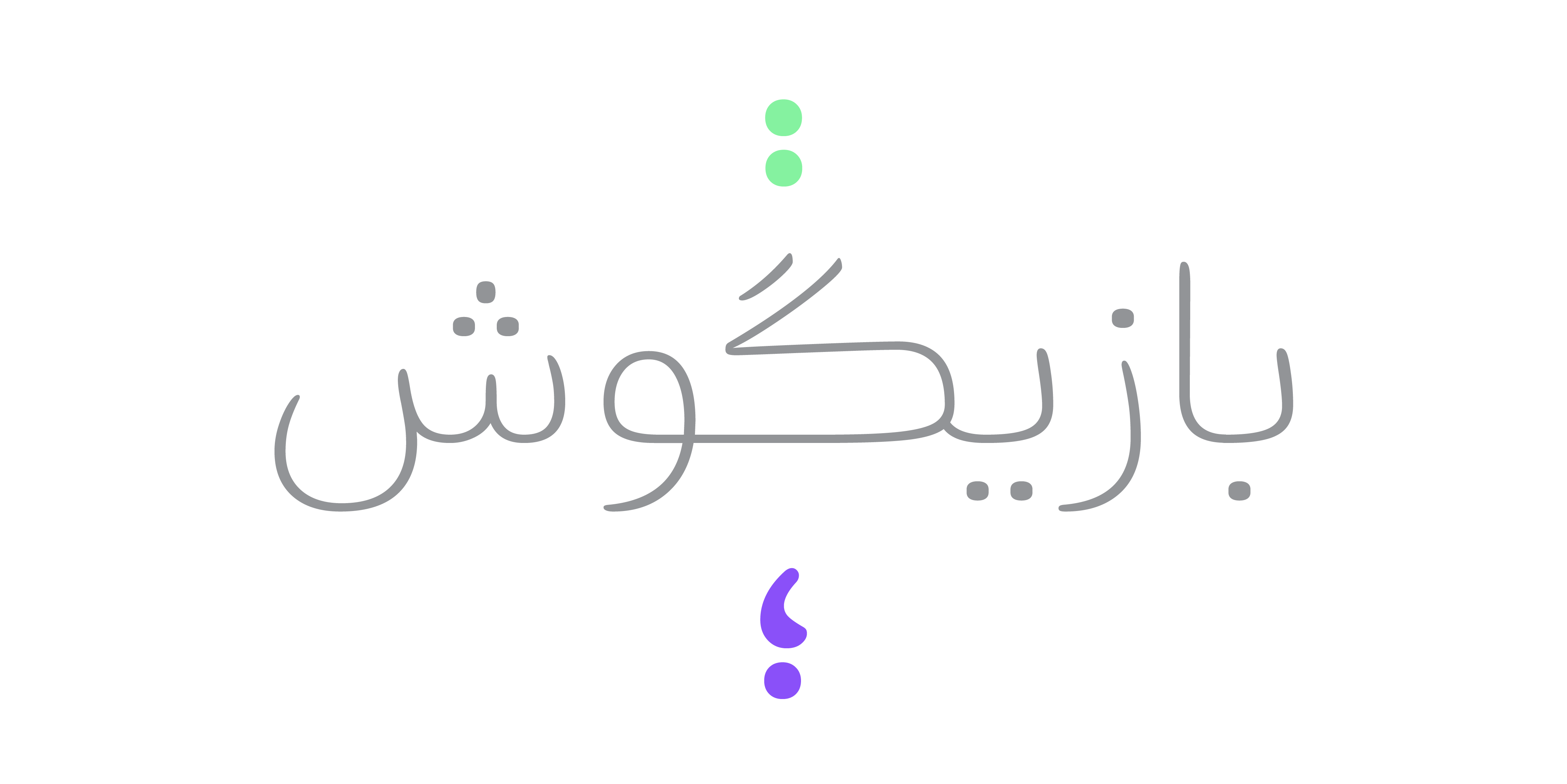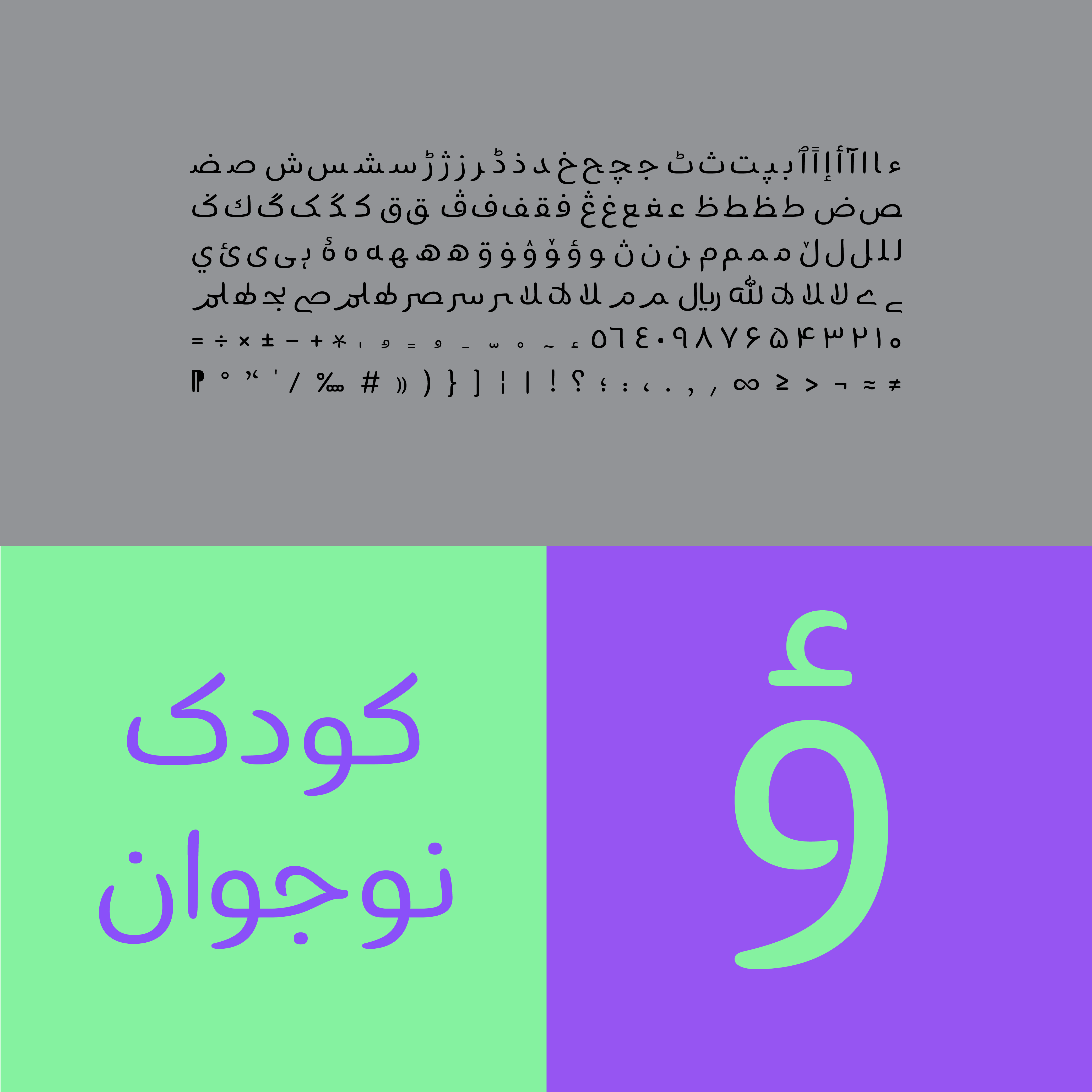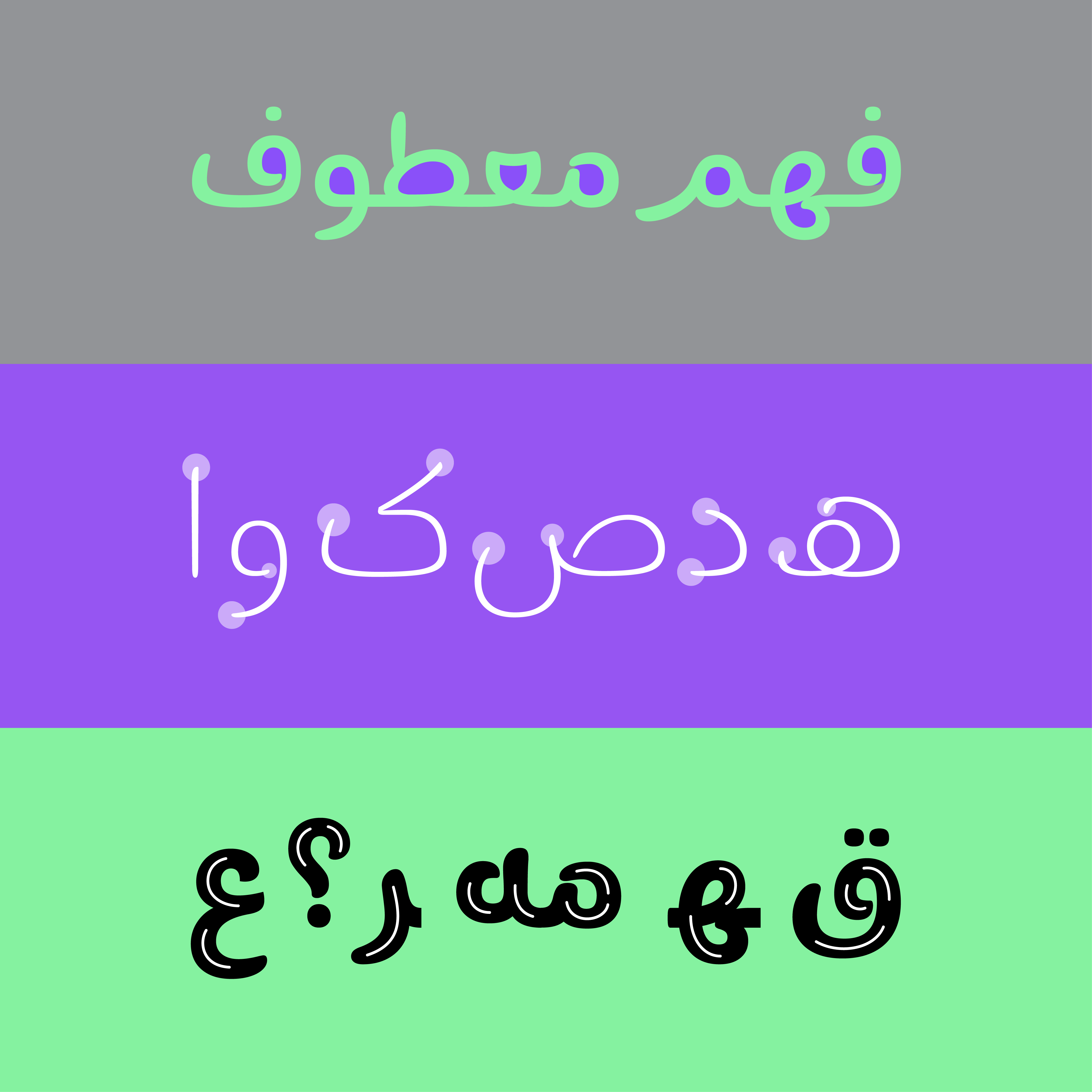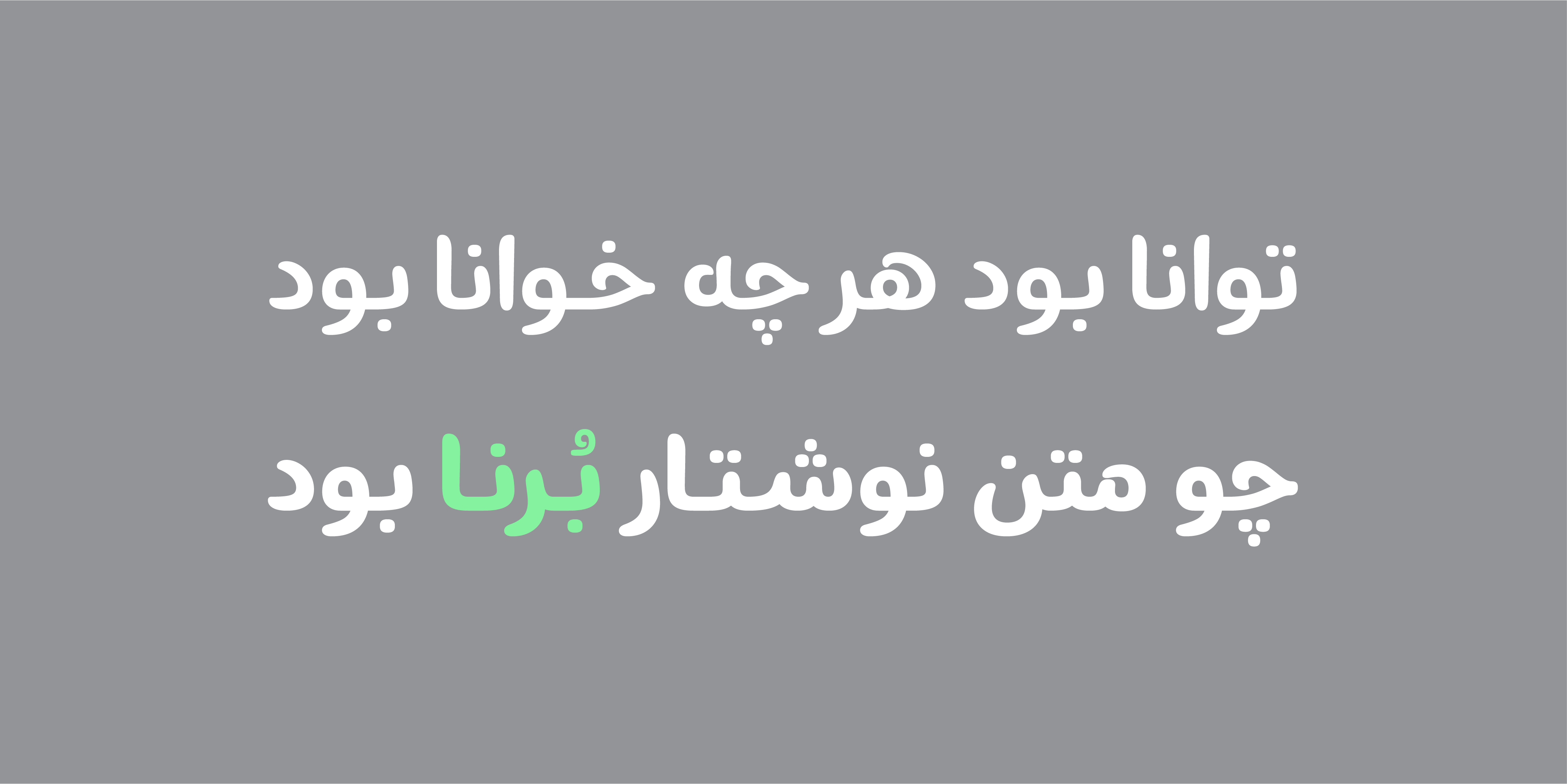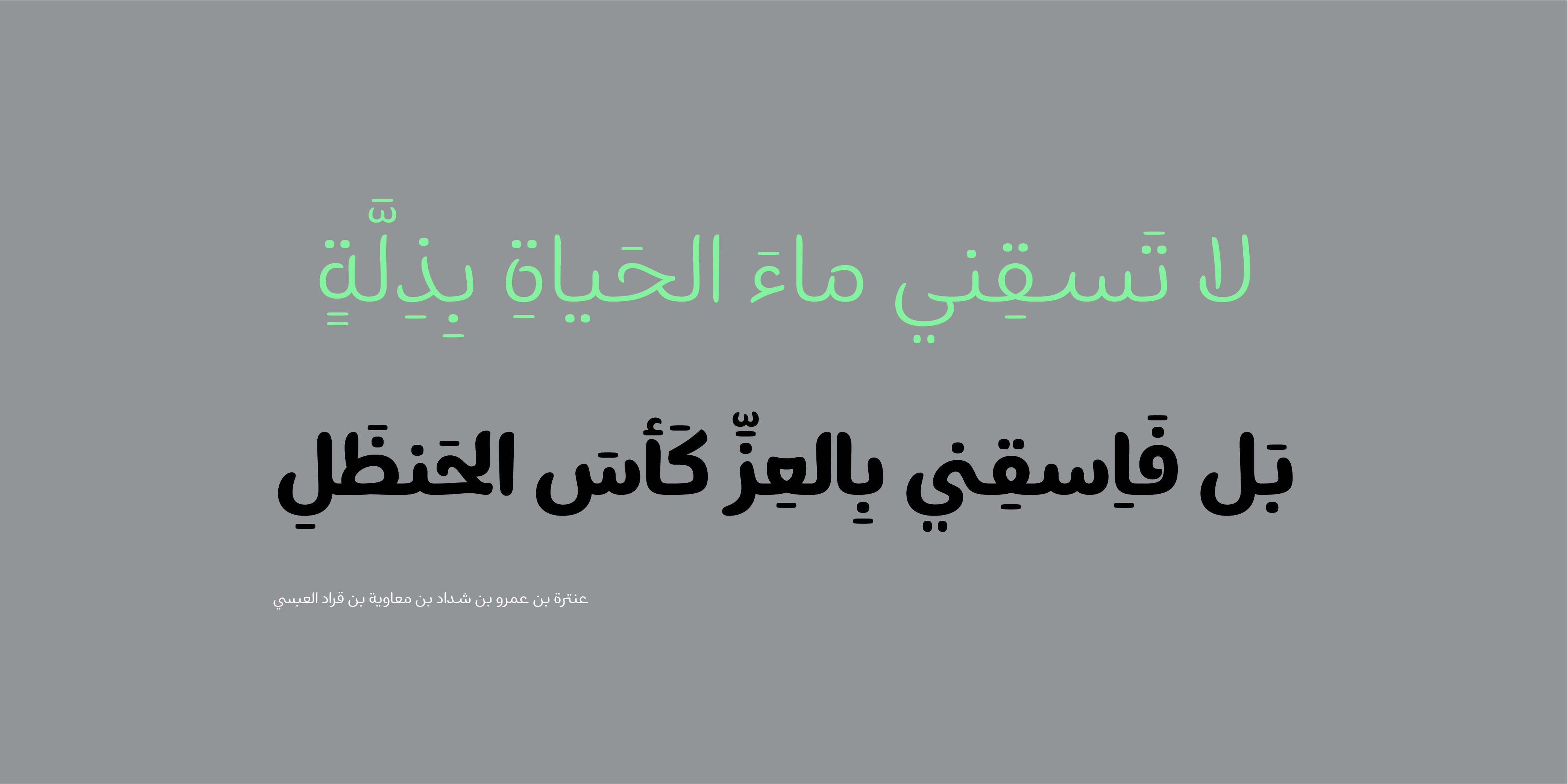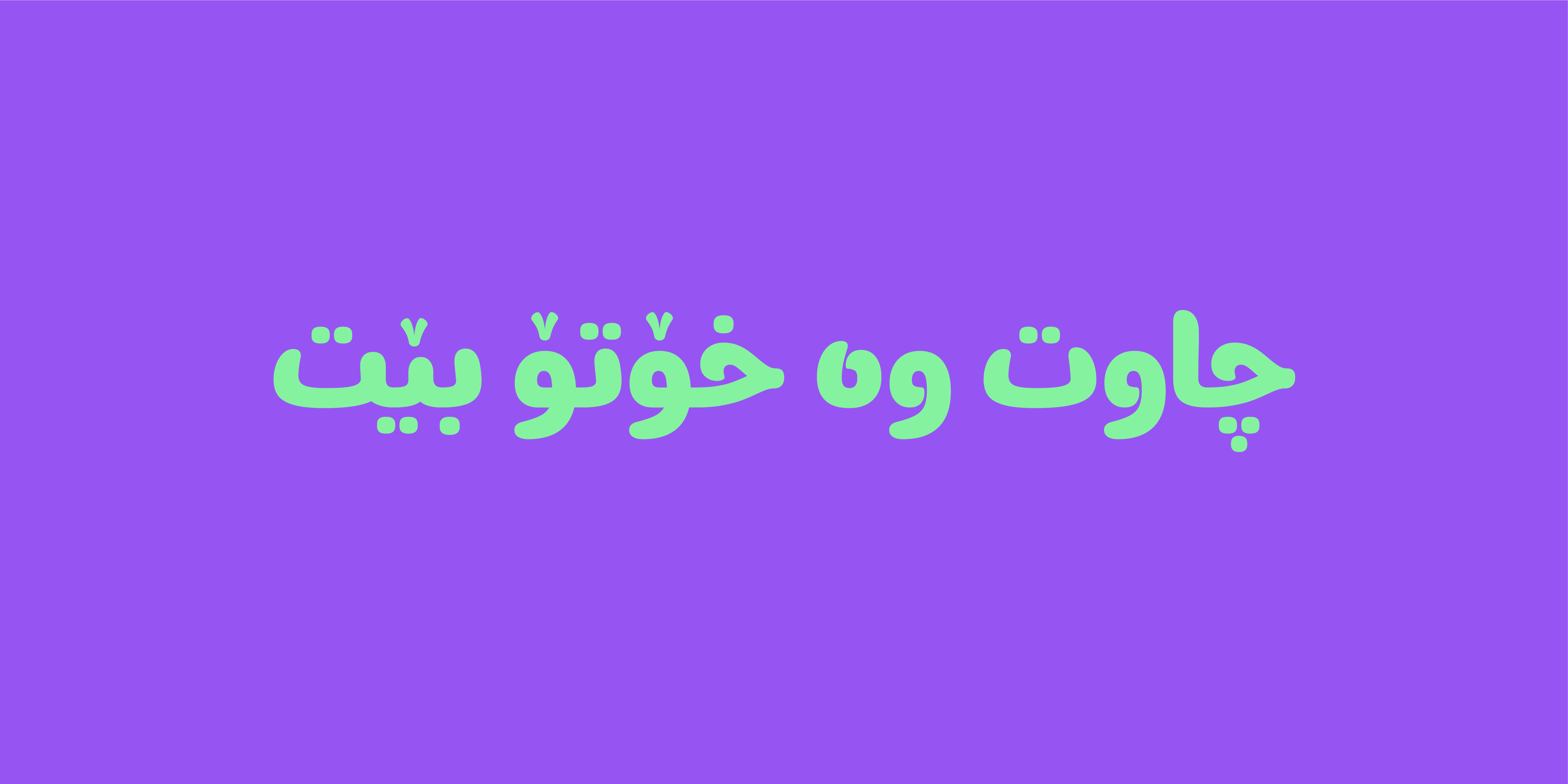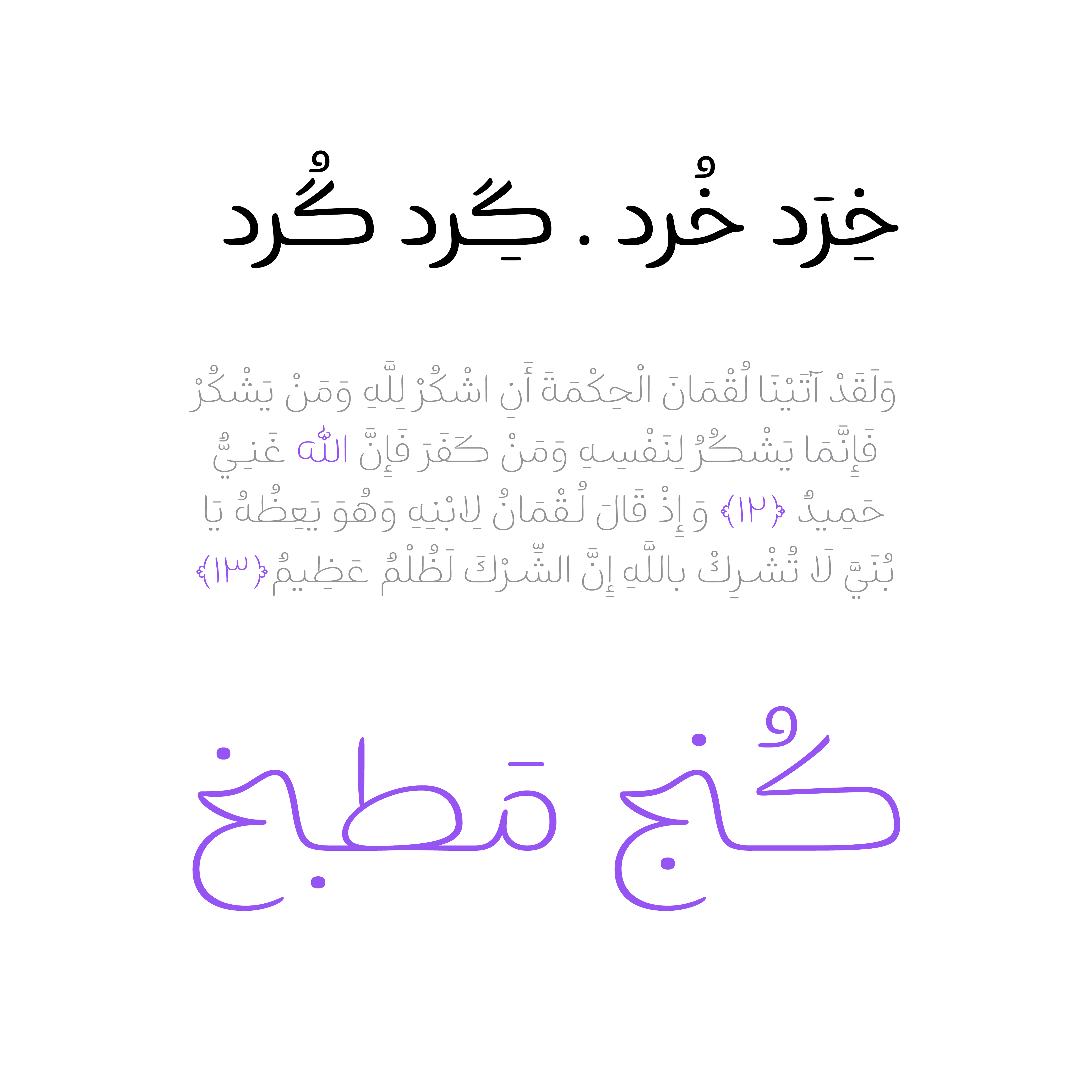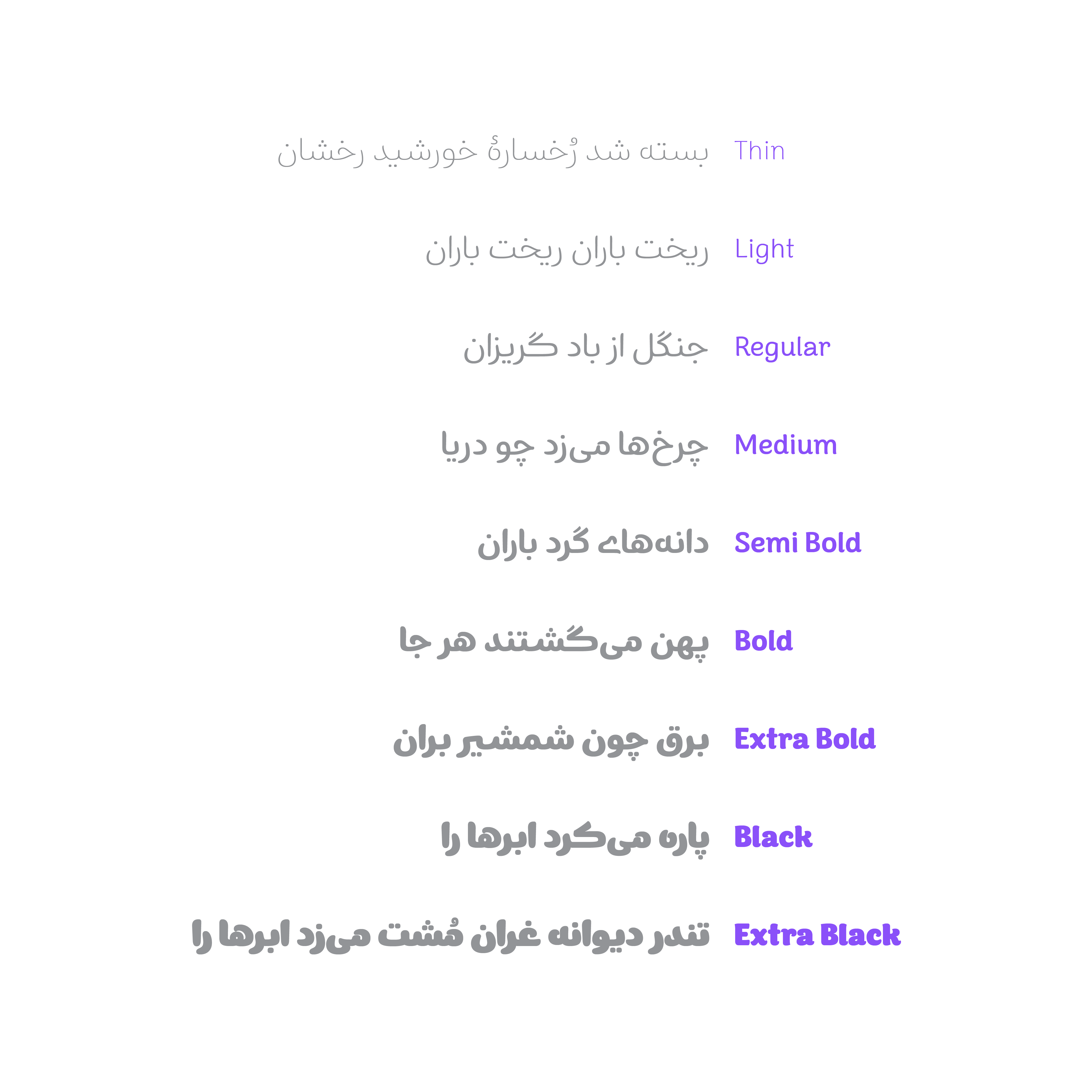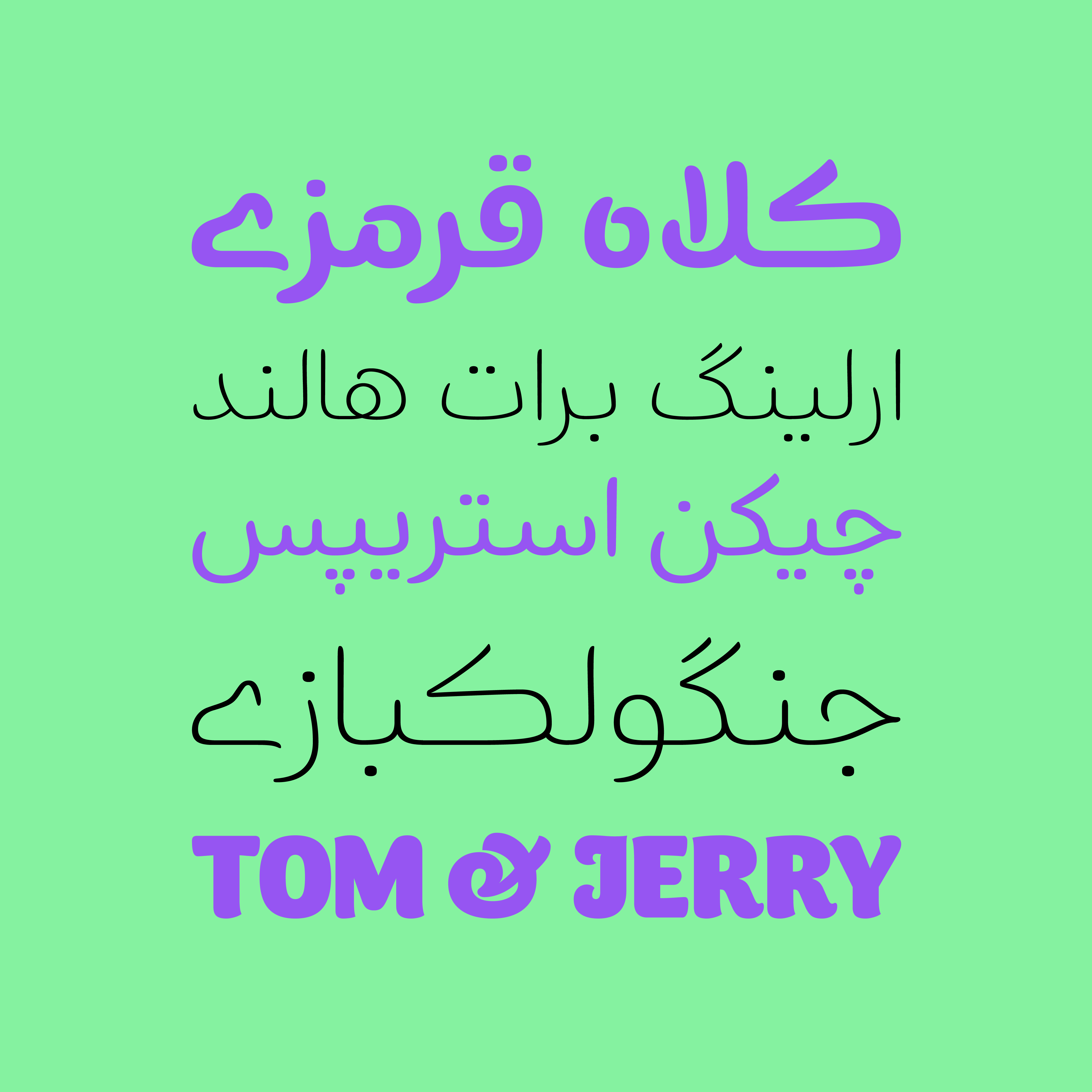
جست و خیز در دندانهها، چرخش در کاسهها، پیچ و تاب در فرمها و درشت بودن چشمها حس پویایی و جنب و جوش را به فونت داده است.
فاقهای باز، دور زیاد حروف نسبت به سطح آن و فرمهای سیال، از ویژگیهای دیگر بُرنا است.
طراحی فرمهای کشیده در برخی حروف و جایگزینهای پرکاربرد، ترکیبهای متنوعی را در اختیار طراحان قرار میدهد.
کنتراست ضخامت بصورت معکوس طراحی شده تا با نوشتار لاتین هماهنگ باشد و هارمونی بیشتری را در متنهای دو زبانه ایفا کند.
فونت لاتین Arima Madurai برای همراهی با بُرنا انتخاب شده و در جهت هماهنگی بیشتر سایر وزنها نیز بازتولید شدهاند.
امکان تغییر رنگ در حرکتگذاری روی حروف کمک میکند تا عبارتها و جملات زیباتر به نظر برسند.
فونت بُرنا با 9 وزن «Thin, light, Regular, Medium ,Semi Bold ,Bold, Extra Bold, Black, Extra Black» زبانهای عربی، کردی و اردو را نیز پوشش میدهد.